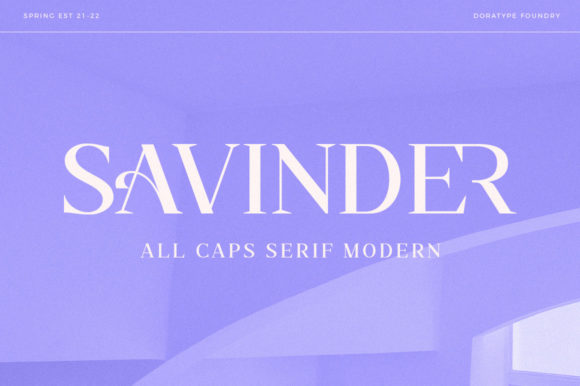
Savinder - элегантный и стильный шрифт serif.
Его легко подогнать под невероятно большой набор проектов, так что добавьте его к своим творческим идеям и заметьте, как он выделяет их!